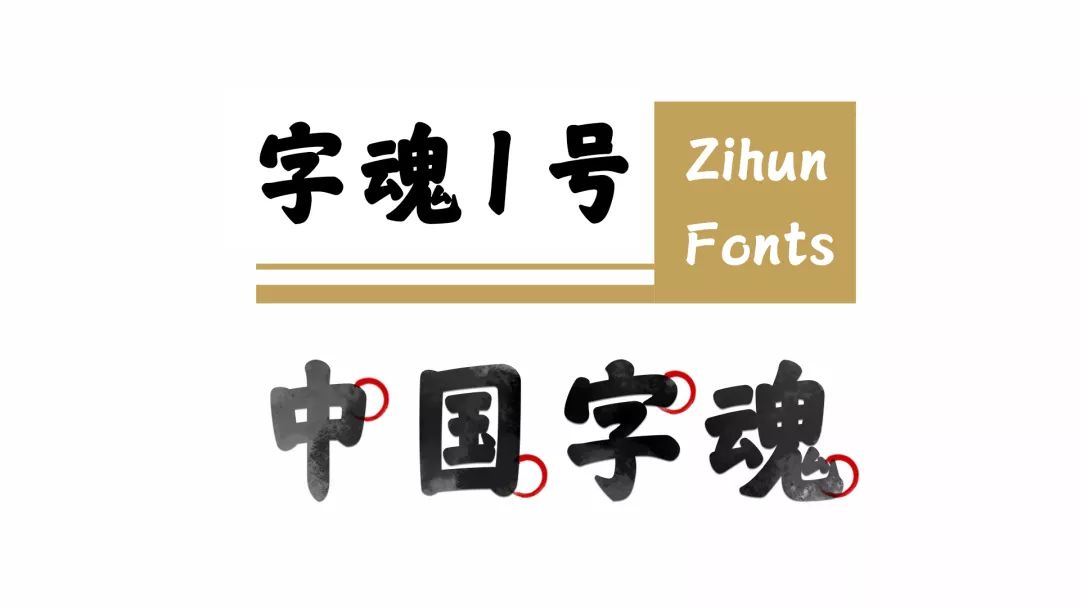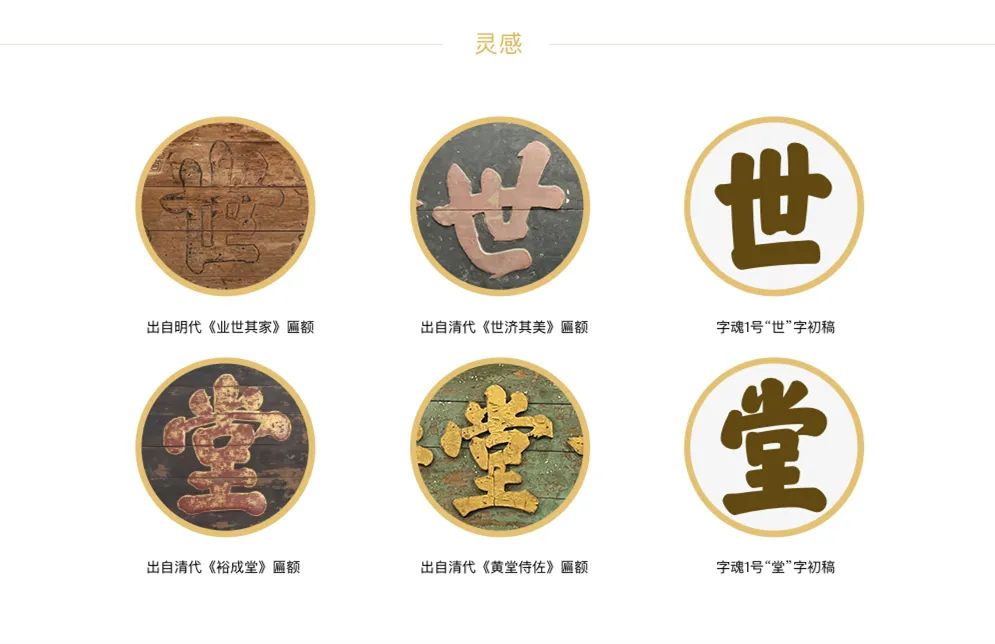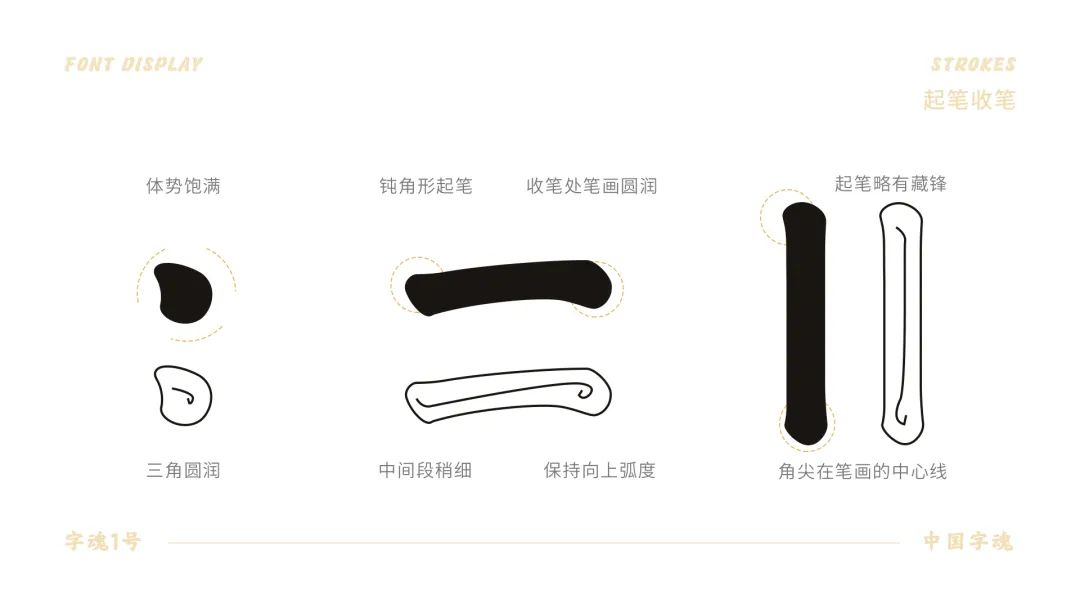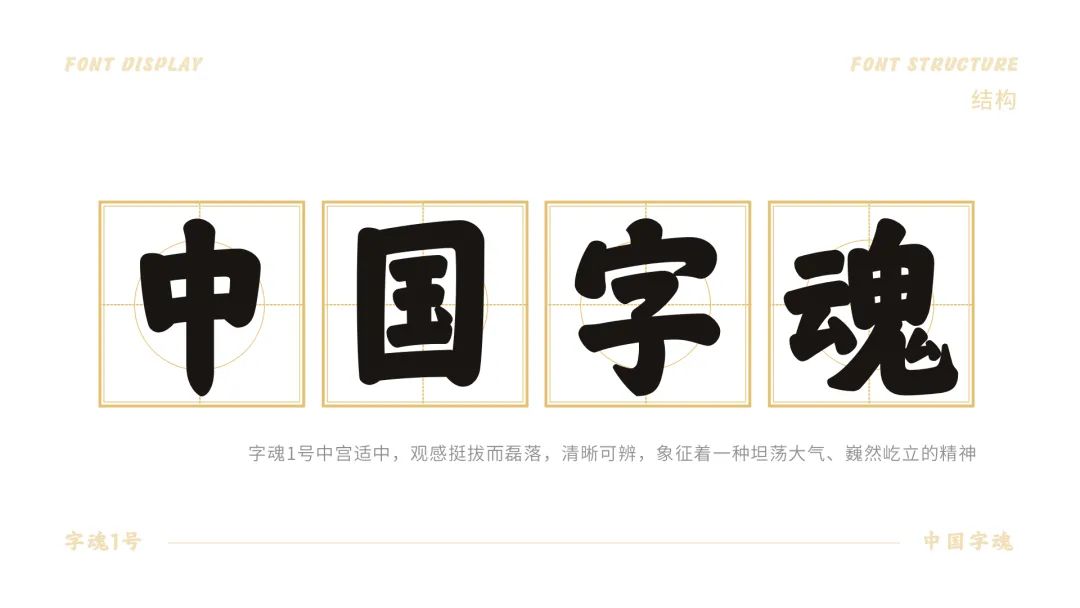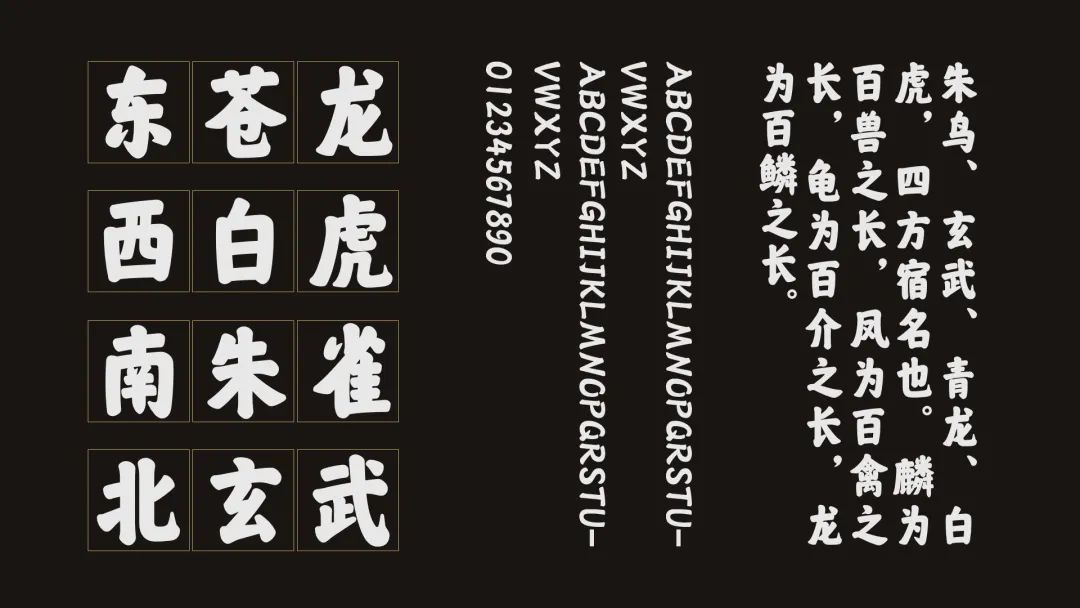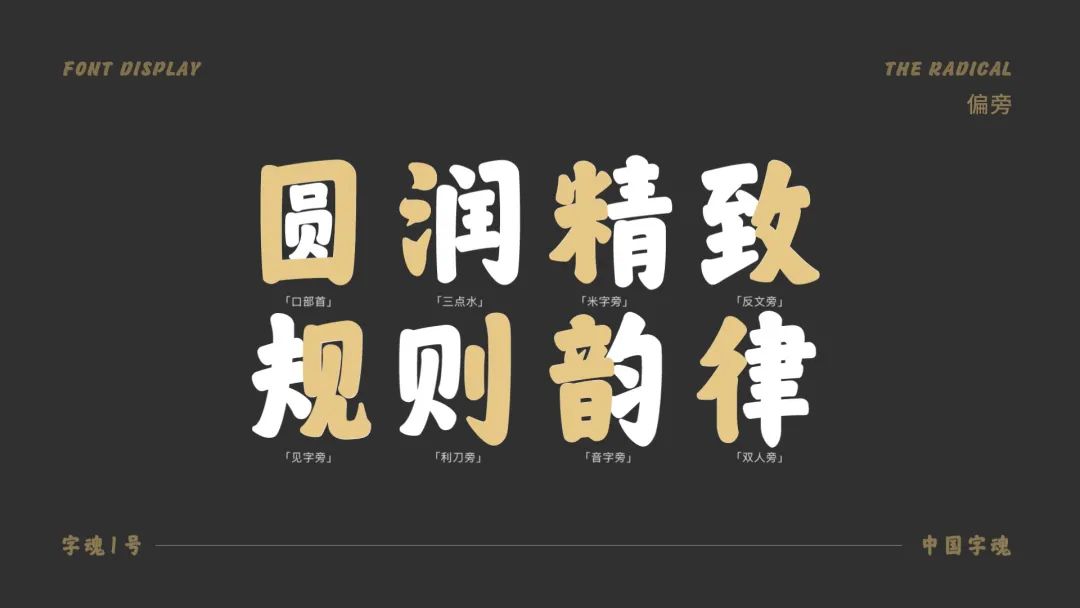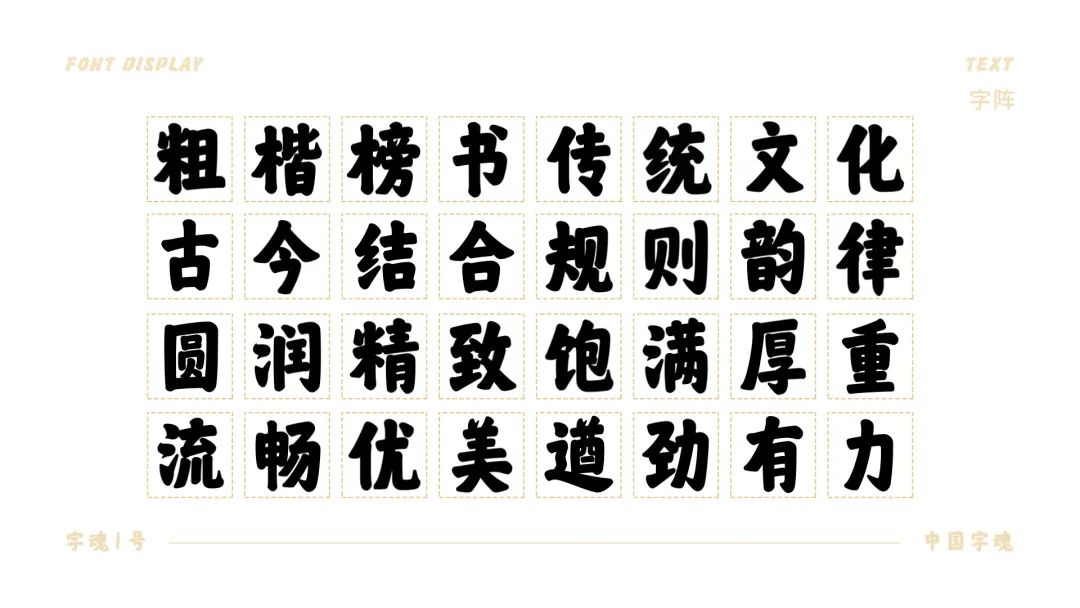
“ 字形灵感
字魂1号-中国字魂的设计灵感来源于榜书、匾额大字。
在缺少传媒的古代,匾额独特的广告、记录、情感表达及社交功能使其很快应用于生活的方方面面。匾额上的大字寄托了人们的祝福、歌颂、抒发壮志等美好情感。
“ 字形介绍
字魂1号 - 中国字魂
以北魏粗楷、匾额榜书为基础风格
笔形圆润精致、饱满厚重;
线条流畅优美、遒劲有力;
结构稳健挺拔、重心稍高;
中宫适中,字体观感清晰;
排版效果醒目、美观、大方;
兼具传统书法的艺术美感。